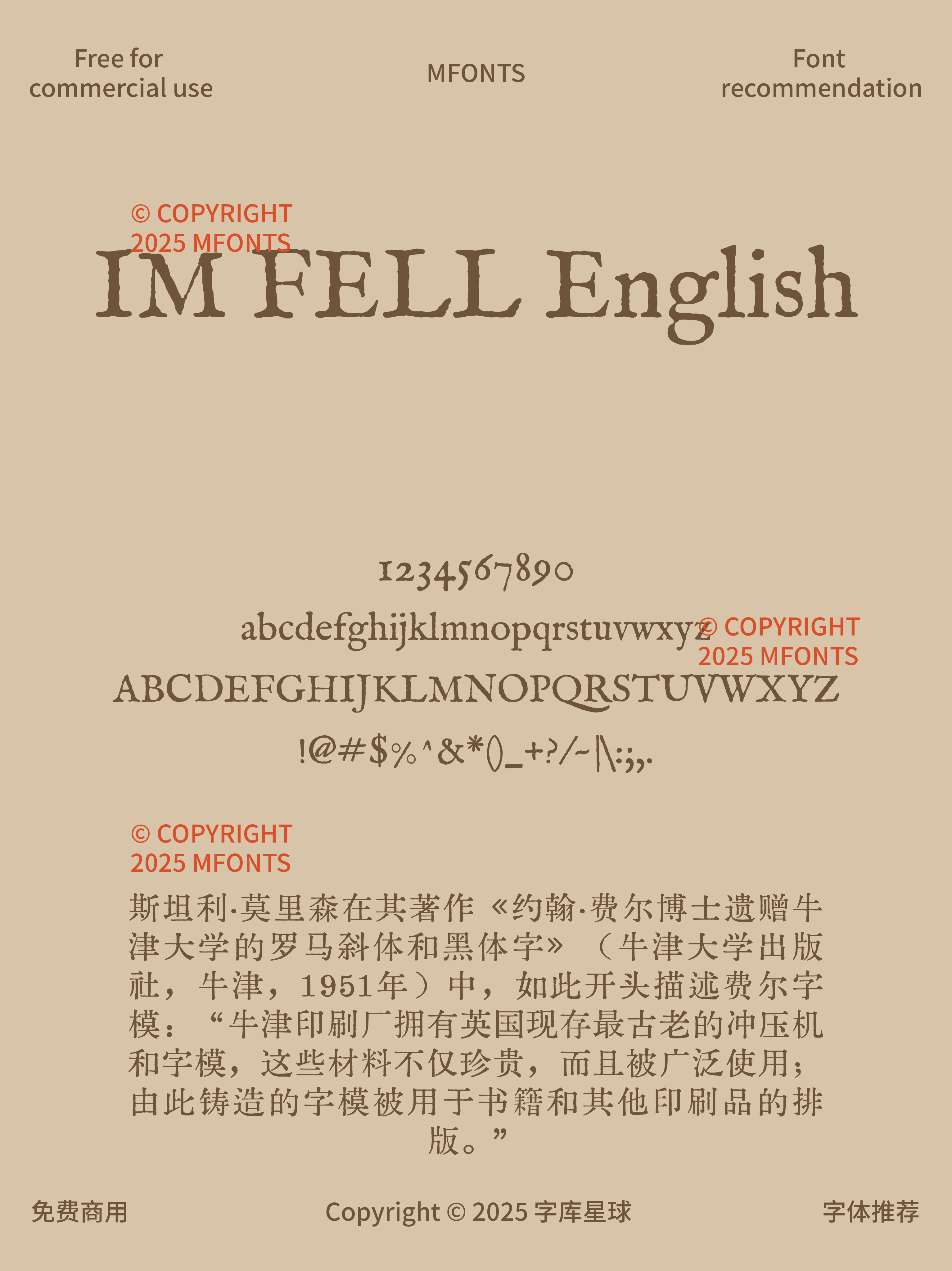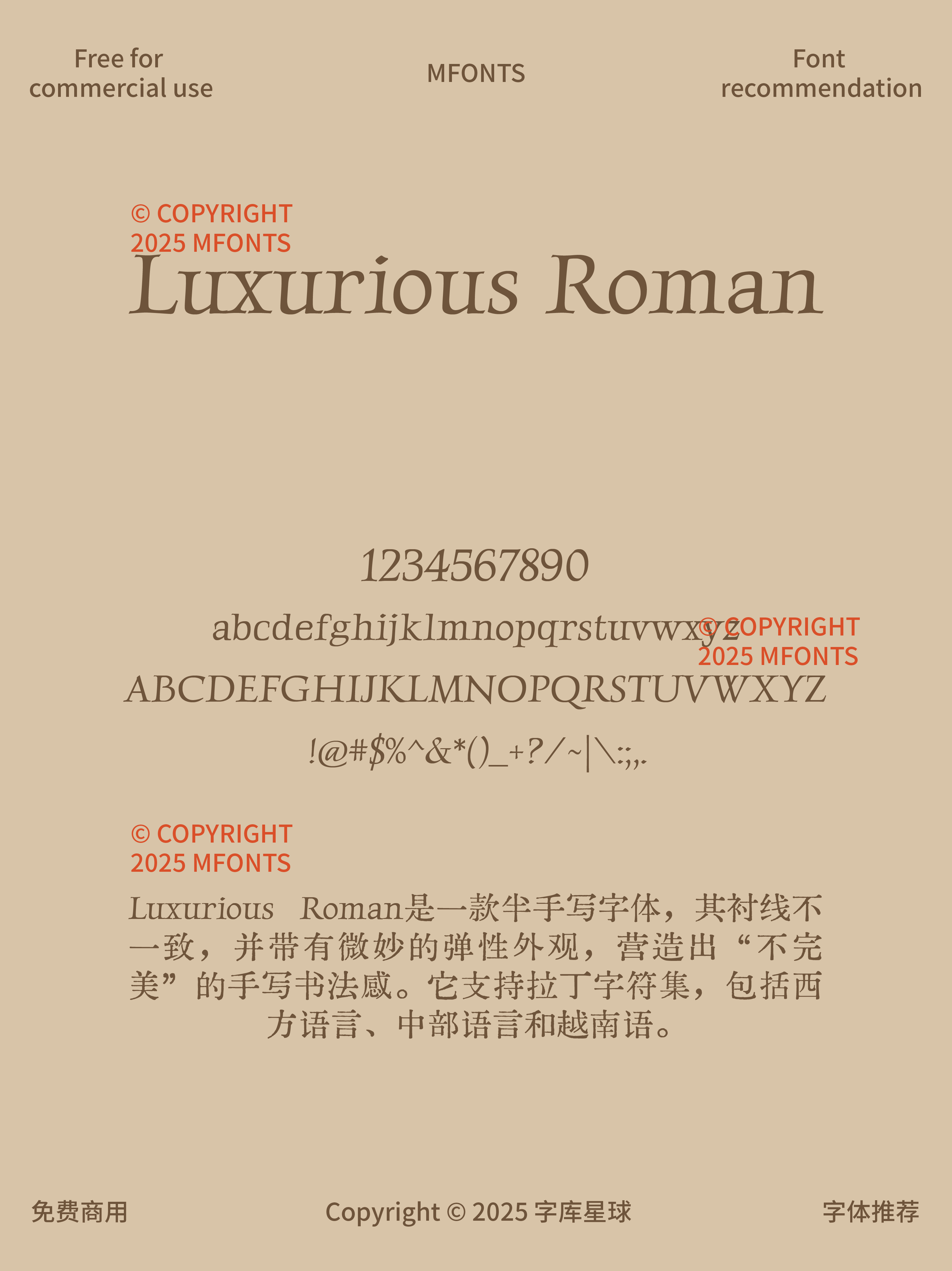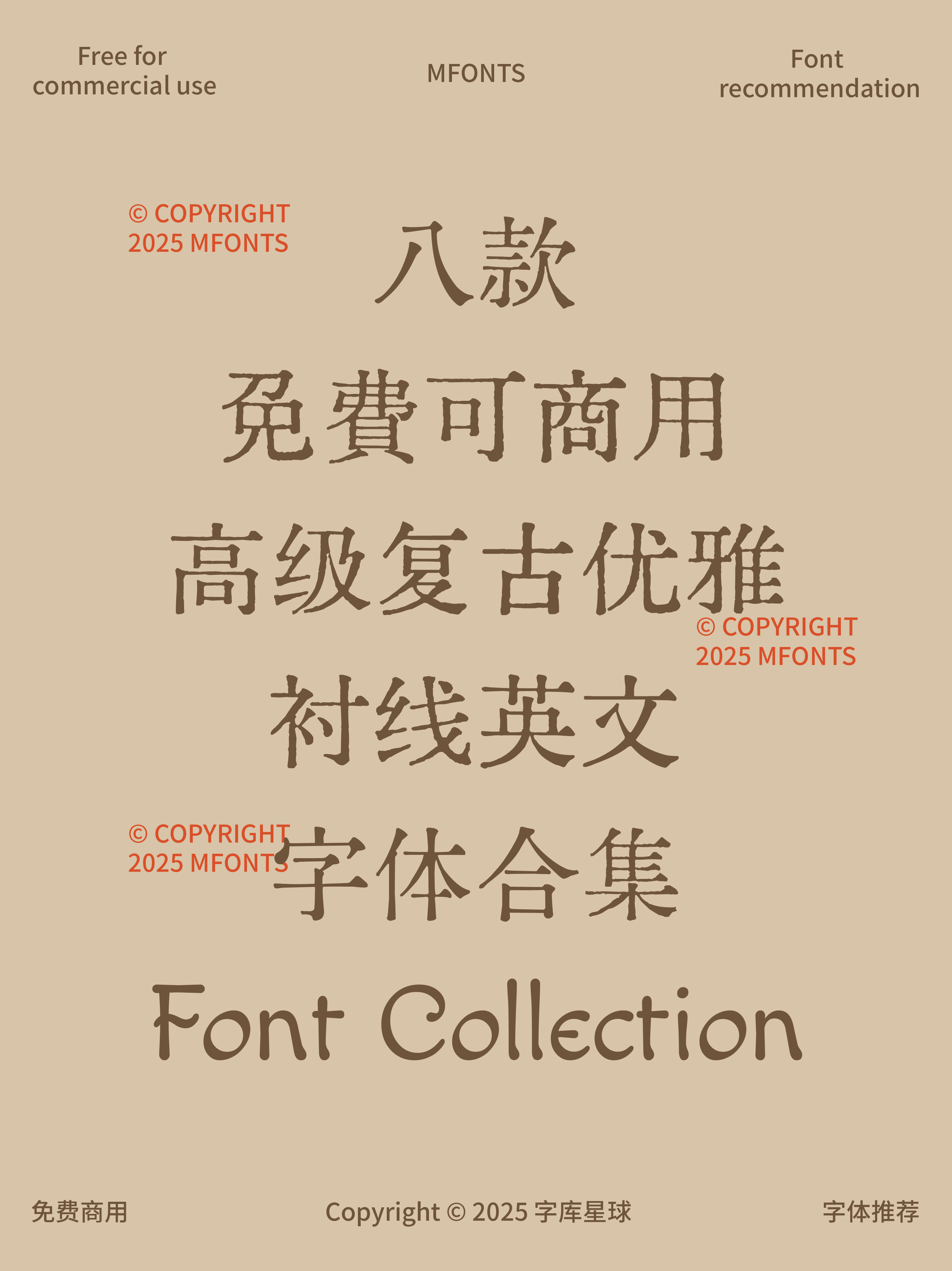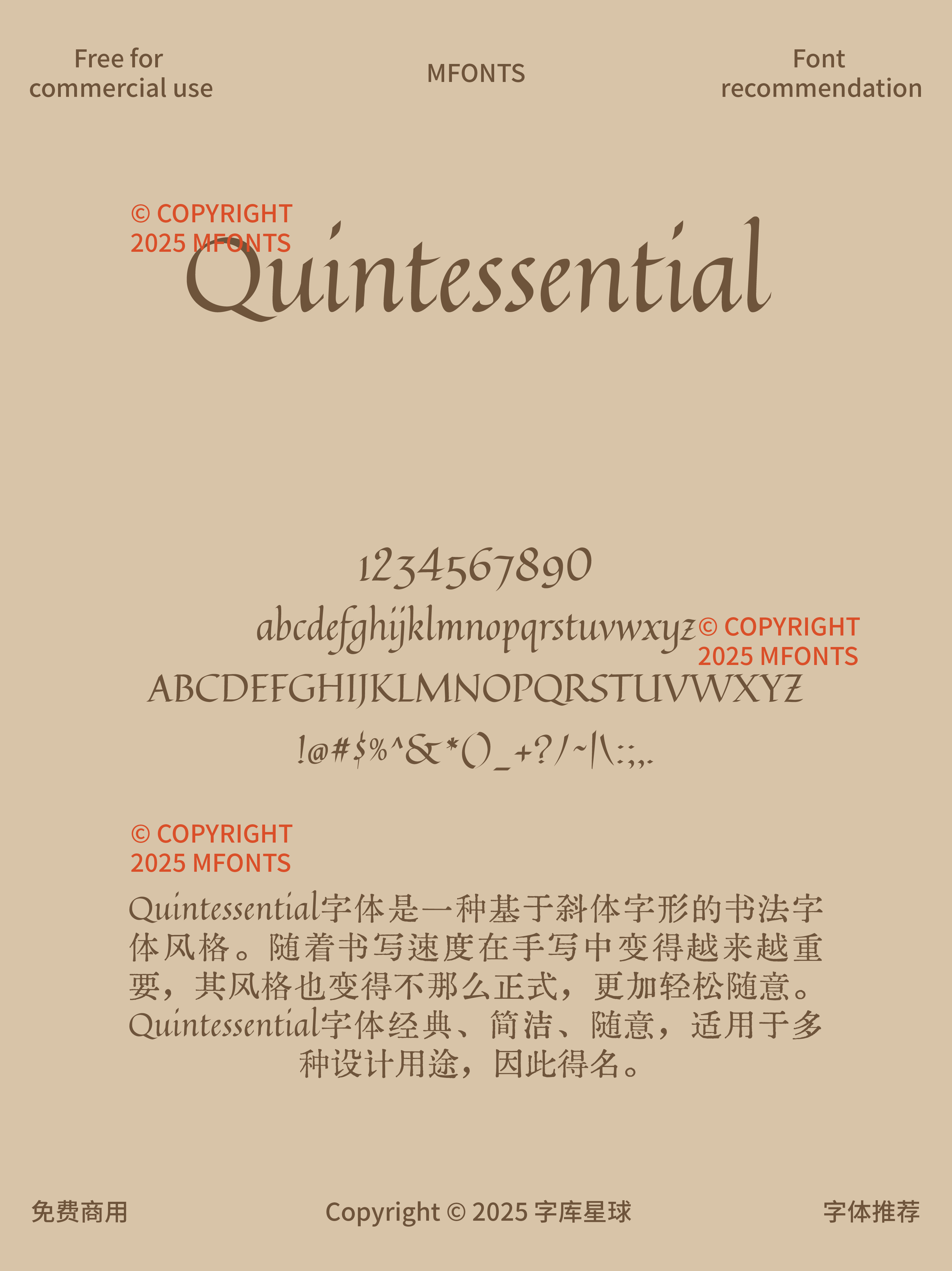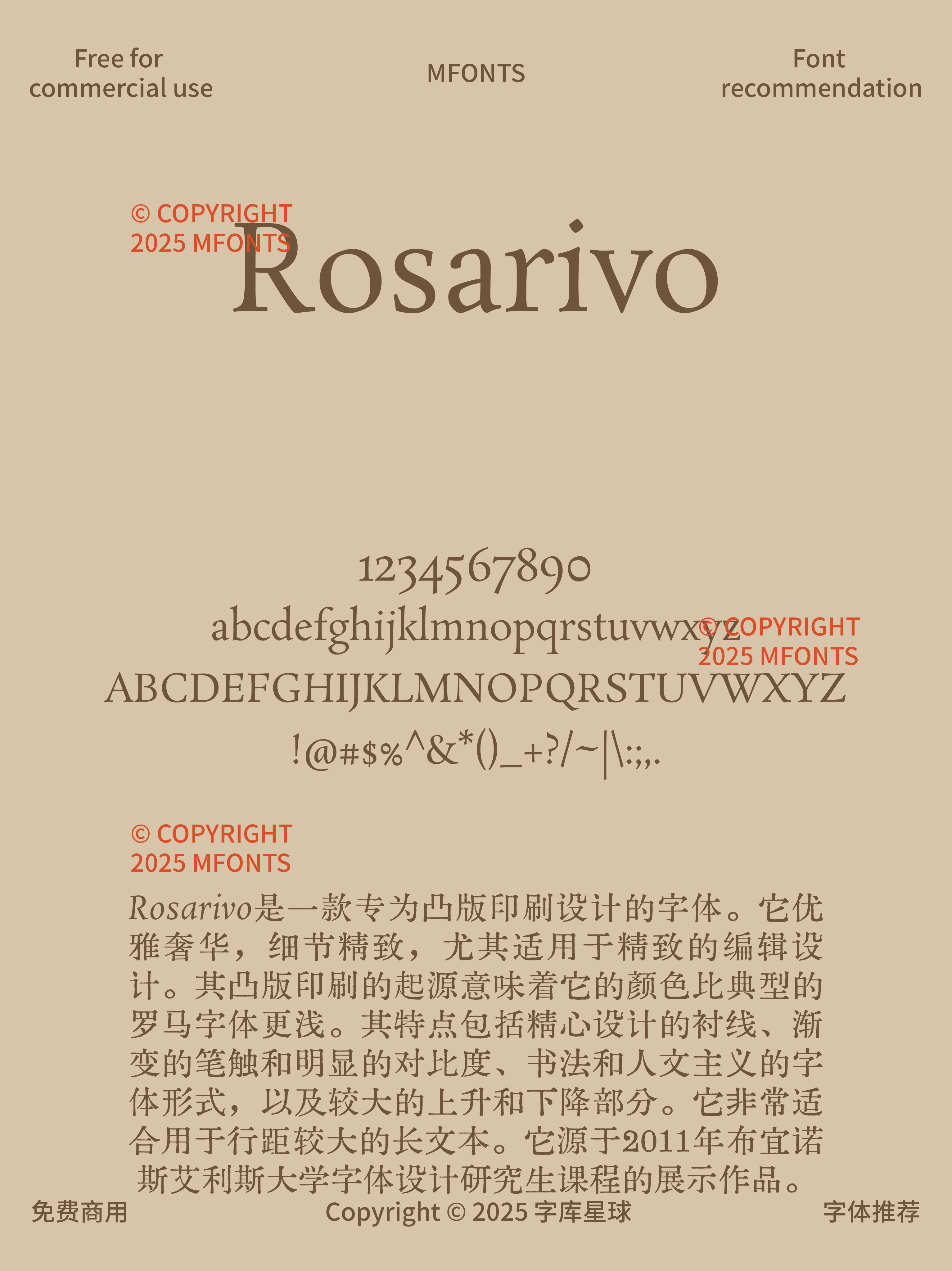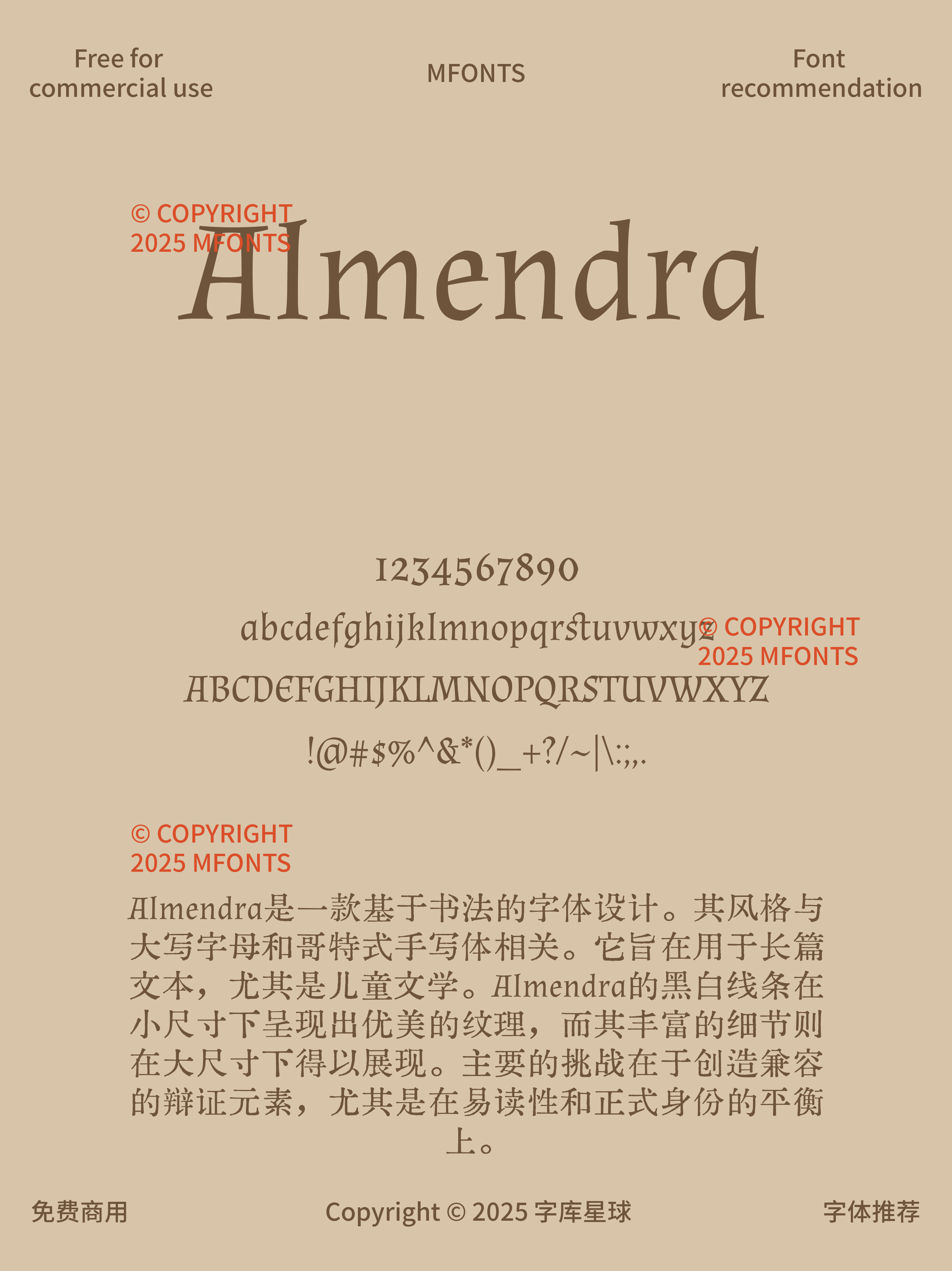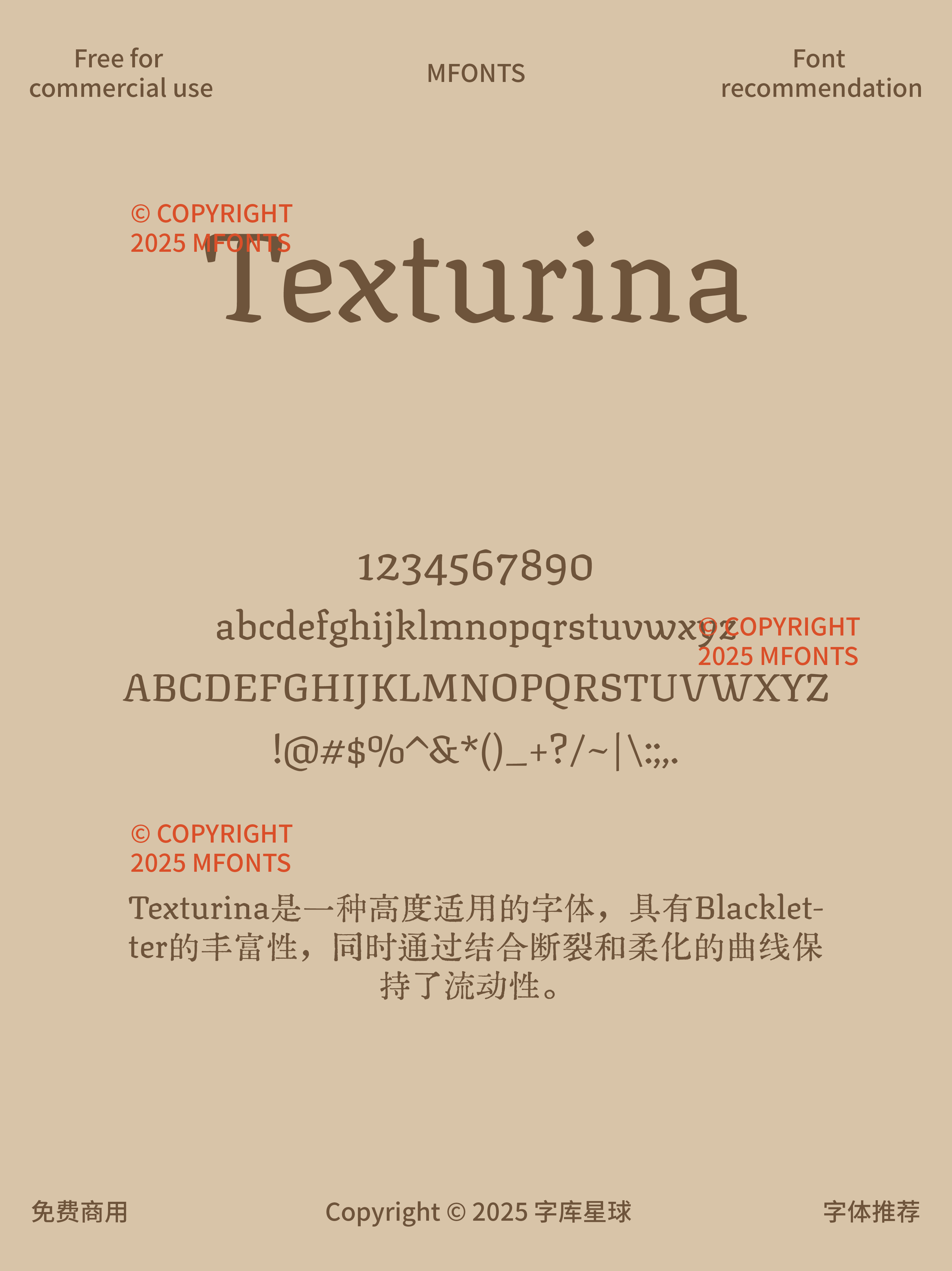
八款免费可商用高级复古优雅衬线英文字体
今天给大家分享 8 款绝美的免费可商用复古优雅衬线英文字体,轻松让你的作品呈现复古感~
高级衬线体,常用于时尚杂志设计。为时尚单品宣传图、美妆海报增添优雅气质,尽显奢华与时尚感。
复古中带有时尚感的衬线体。在复古风格的品牌视觉设计、怀旧主题的海报中,发挥独特魅力,让人回忆起过去的美好时光。